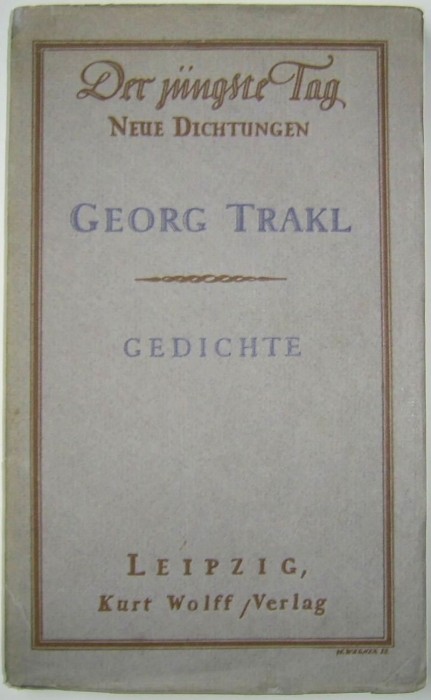
Schrift mit Kurrentanleihen, verwendet 1913
ich suche die schriftart der ersten zeile von diesem buchcover. kennt sie jemand und gibts die auch digital?
Eher nicht, schaut mir sogar nach einem gezeichneten Logo der Buchreihe aus, die beiden e sind leicht unterschiedlich.
Auch in der hier nicht angefragten 2. Zeile „Neue Dichtungen“ sind deutliche unterschiede in gleichen Buchstaben zu finden, sodass ich annehme, dass der gesamte Reihentitel von einem Grafiker gezeichnet, und lediglich der hier blaue Text gesetzt wurde.